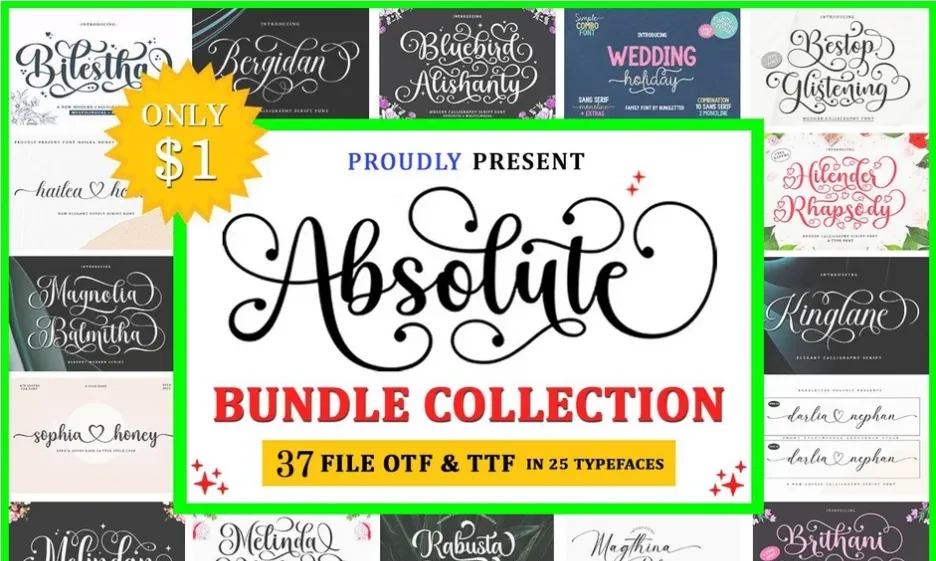
嘿,有创意的灵魂!👋 你准备好将你的设计水平提升到下一个层次了吗?今天,我们将深入探索绝对庞大的刷子包合集第162部分,相信我,这就是字体排印的金矿。无论你是品牌设计高手、网页设计师,还是仅仅喜欢玩弄漂亮字体的人,这20个字体包即将成为你的新挚友。🚀✨
为什么要使用这些字体包?
说真的——字体是设计界默默无闻的英雄。它们营造氛围、讲述故事,让你的作品看起来专业(或俏皮、优雅、前卫)。选对字体,一个简单的logo也能成为经典。有了这些字体包,你买的不仅仅是字体,而是投资了一个充满无限创意可能的工具箱。而且,你的钱花得超值——相当于用买一个甜甜圈的钱,换来一整家烘焙坊的甜甜圈。🍩🎨
精选20大字体包推荐
绝妙字体包
这个字体包简直燃爆了!🔥 从优雅的衬线字体到俏皮的手写体,这种风格混合几乎能拯救你任何项目。品牌设计、网页制作、印刷品——统统搞定。
绝对字体合集
这是一个绝对不能错过的宝藏。💎 它精心融合了衬线体、无衬线体、手写体和展示字体。当你需要为项目增添”惊艳”效果时,它绝对是不二之选。
Anethalia – 婚礼字体 Hq4W23W
正在策划一场婚礼或一个浪漫项目?💍 这款优雅的手写字体堪称精致的代名词。它非常适合用于邀请函、婚礼预告,能为您的作品增添迷人而个性化的触感。
All In 系列字体捆绑包
这款合集完全名副其实——一站式满足你的所有需求。🃏 包含衬线体、手写体、无衬线体和展示字体,让你永远不缺选择。
40+ 字体合集
超过 40 种独特字体?是的,请收下!🎉 这个多样化的合集包含多种字重和高质量格式。是任何设计师工具包中的真正利器。
超棒字体合集 – 390 款高级字体
390 种字体?!这可不是一个字体包,这是一个完整的字体库。📚 这个庞大的合集非常适合机构工作,也适合任何希望拥有无限多样字体的个人。简直太划算了。
Beauty Craft 字体包
致所有美妆与生活方式设计师!💄 这款优雅手写体与经典无衬线字体的合集,专为打造时尚精致的品牌形象而设计。
Fontasix 合集 Vol 1
这一卷简直棒极了!🌟 它融合了优雅的衬线字体、现代的无衬线字体以及俏皮的手写字体。当你想要一点多样选择时,效果非常出色。
全部合集套装
全力以赴,尽享这套全面的素材库!🚀 它不仅仅是字体——还有高清设计元素,能提升您的印刷或数字项目品质。
字体套装合集
经典之选!🏆 这套精心挑选的衬线字体、手写字体和展示字体,是您在每个项目中都能信赖的可靠工具。
Fontbundles – Cucciolo 字体及附加包
这款实在太好看了!🐶 Cucciolo 意为“小狗”,这款俏皮、充满奇思妙想的字体,将为你的品牌设计、海报或儿童项目增添无限个性。
Awesome Font Bundle Vol 01 – 20款高级字体合集
一套小巧而精致的20款高级字体合集。🌈 从优雅的衬线体到现代的無衬线体,本系列非常适合追求品质与多样性、又不想眼花缭乱的设计师。
48款精彩字体合集
48款超棒字体,纯粹惊艳!🚀 这套字体完美适配UI/UX设计师——涵盖网页、印刷和品牌设计。每一种心情,都能找到合适的风格。
超值字体包 – 20款全新字体合集
新鲜出炉!📰 这20款全新字体已准备就绪,让您的下一个项目看起来格外新颖且现代。包含多种字重,用途广泛。
全部字体合集 – 巨型字体系列包
要么全力以赴,要么回家躺平!🏠 这个巨型字体系列无所不包——衬线、无衬线、手写体和展示字体,是专业设计师的完整排版工具包。
精美字体超级合集
顾名思义,这些字体简直美不胜收。🌸 非常适合博主、创作者以及任何希望文字如艺术品般呈现的人。
一切所需套装
老实说?它的名字已经说明了一切!🧰 这个全面的套装包含图形和字体——创意专业人士将项目变为现实所需的一切。
精美字体合集 – 40款字体
40款独特字体,激发无限灵感!✨ 从现代无衬线体到经典衬线体,这套合集是每位设计爱好者的完美入门包。
90+ 字体包
90+ 款字体,基本上让你一辈子都用不完!🎪 这个庞大的字体包包含多种字重和样式,让你尽情尝试各种创意。
超值套装
最后但绝对不容错过!🌟 这套综合包包含高分辨率图形、插图和多种风格,是您数字工具箱的终极补充。
总结
哇,真是一段精彩的旅程!🎢 Brushespack 系列第162部分绝对满载字体宝藏,能让您的设计熠熠生辉。无论您是在寻找包含390种字体的庞大库,还是婚礼所需的精美手写体,这里都能满足您的需求。别等太久——赶紧挑选您的最爱,让创意尽情驰骋吧!🖌️🎨